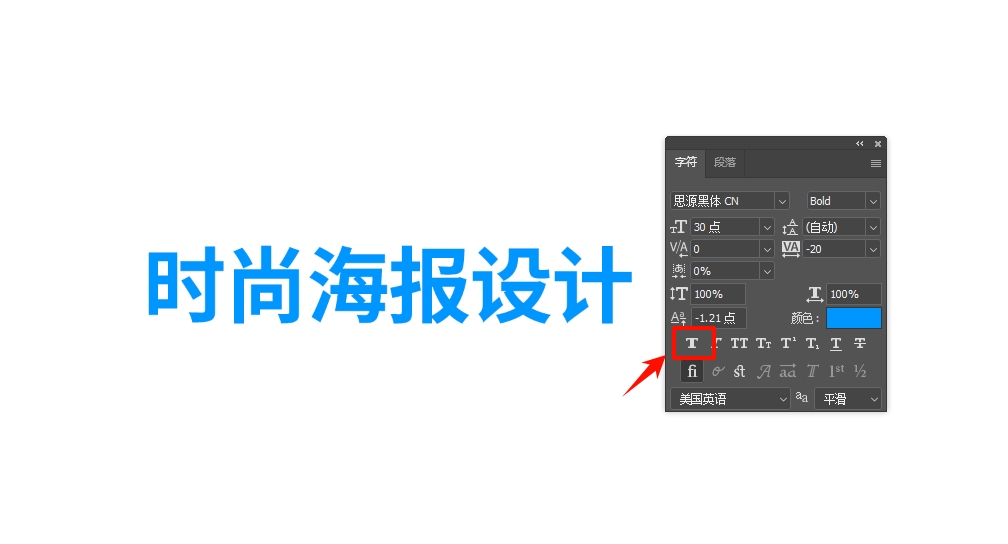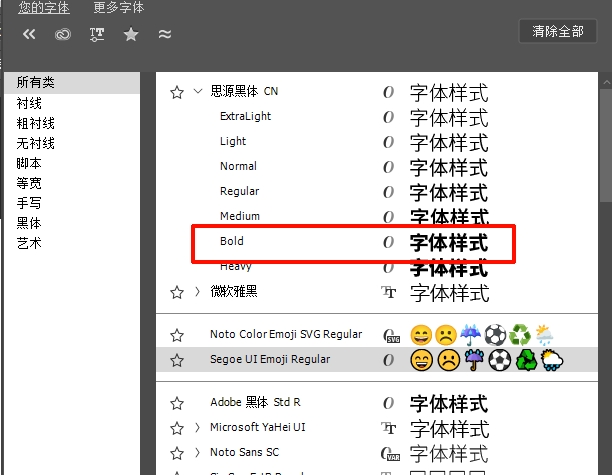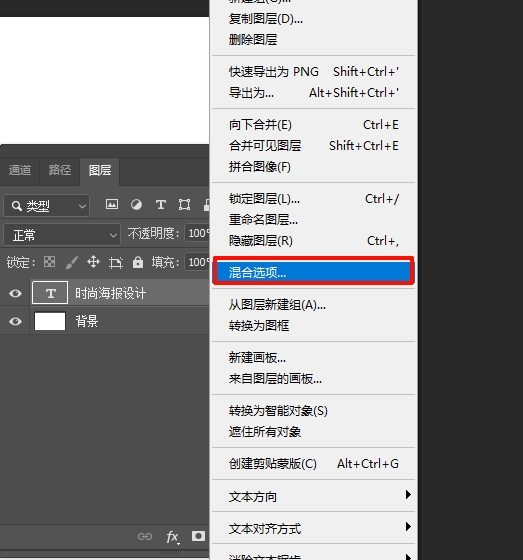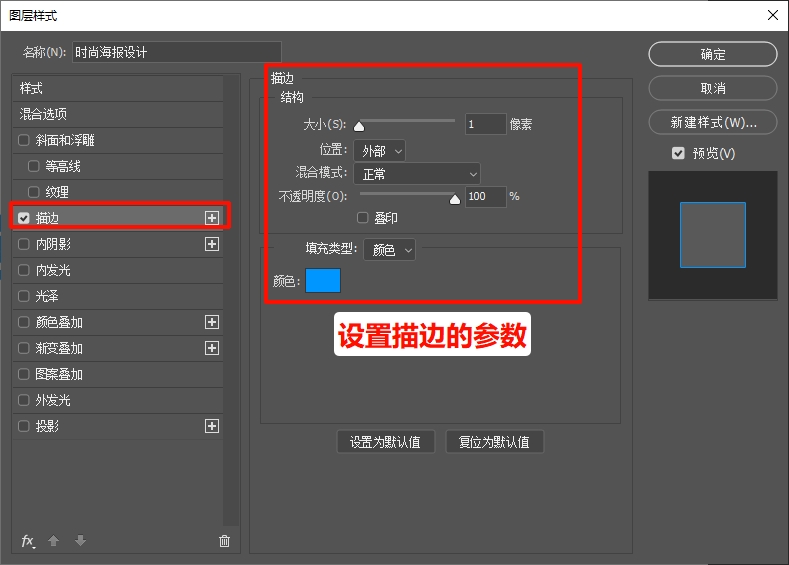
ps怎么字体加粗?ps加粗字体的5种方法
ps 字体怎么加粗?海报设计、图文排版、宣传物料制作过程中,字体加粗是使用频率极高的基础操作,加粗文字能够强化视觉层级、突出页面核心信息,提升画面整体表现力。本文整理5种 PS 文字加粗实操方法,适配不同设计质感与使用场景,同时搭配StartAI Banana 修图辅助设计方案,简化文字特效制作流程,兼顾出图效率与文字精致质感。
PS加粗字体的5种方法
方法一:字符面板一键仿粗体(新手快速通用)
该方法无需字体自带粗体字重,一键开启仿粗体效果,操作简单,适合日常快速排版、临时文字加粗需求。
1、打开 PS 软件,新建画布或导入设计素材,选中需要加粗处理的文字图层;
2、点击顶部菜单栏【窗口】,下拉选择【字符】,调出字符调整面板;
3、框选目标文字内容,点击面板内仿粗体功能按钮,即时完成文字加粗,调整完成直接确认即可。
适用场景:无原生粗体字重的字体、日常简易图文排版、临时快速加粗。
方法二:字体原生粗体样式(质感最优,专业设计首选)
多数商用字体自带 Bold、粗体、Black 等原生字重,相比仿粗体线条均匀、无变形,对画面质感要求高的海报、品牌物料优先选用。
1、选中文字图层,按下快捷键 T 激活文字工具;
2、在顶部属性栏字体下拉菜单,找到当前字体配套粗体样式,标注为 Bold、粗体、黑体、Black 的选项;
3、点击对应粗体样式,文字自动切换原生加粗效果,字体质感自然流畅。
适用场景:品牌海报、印刷物料、高精度商业设计,追求均匀细腻的加粗文字效果。
方法三:图层样式外部描边加粗(自定义粗细,创意海报专用)
通过图层描边实现自定义加粗厚度,可自由控制文字粗细,适合大标题、活动海报、创意视觉字效制作。
1、选中待加粗文字图层,双击图层空白区域,或右键图层选择【混合选项】,打开图层样式面板;
2、勾选左侧列表中的【描边】选项,描边位置设置为外部,匹配文字本体颜色;
3、拖动大小滑块调整描边粗细,数值越大文字视觉越粗,参数调试完成点击确定保存效果。
适用场景:宣传海报、大标题视觉字、需要厚重文字效果的创意设计。
方法四:复制图层叠加加粗(应急简易加粗,无参数门槛)
缺少字体、不方便调整图层样式时可应急使用,无需复杂参数设置,快速加厚文字线条。
1、选中文字图层,按下快捷键 Ctrl+J 复制图层副本,多次复制可提升加粗厚度;
2、移动对齐所有文字副本,保证图层无偏移错位;
3、全部图层对齐后,使用快捷键 Ctrl+Shift+E 合并可见图层,完成加厚加粗效果。
适用场景临时应急修图、简单配图文字加厚、无法调整字体样式的素材。
总结
日常简易排版优先使用字符面板仿粗体;商业印刷、精致设计选用字体原生 Bold 粗体;海报大标题厚重字效采用图层样式描边加粗;临时应急修图可使用复制图层叠加方式。若需要批量处理图文、快速优化文字视觉效果,可搭配StartAI Banana 修图插件,依靠 AI 智能调整文字粗细,简化繁琐操作,大幅提升图文排版与设计产出效率。